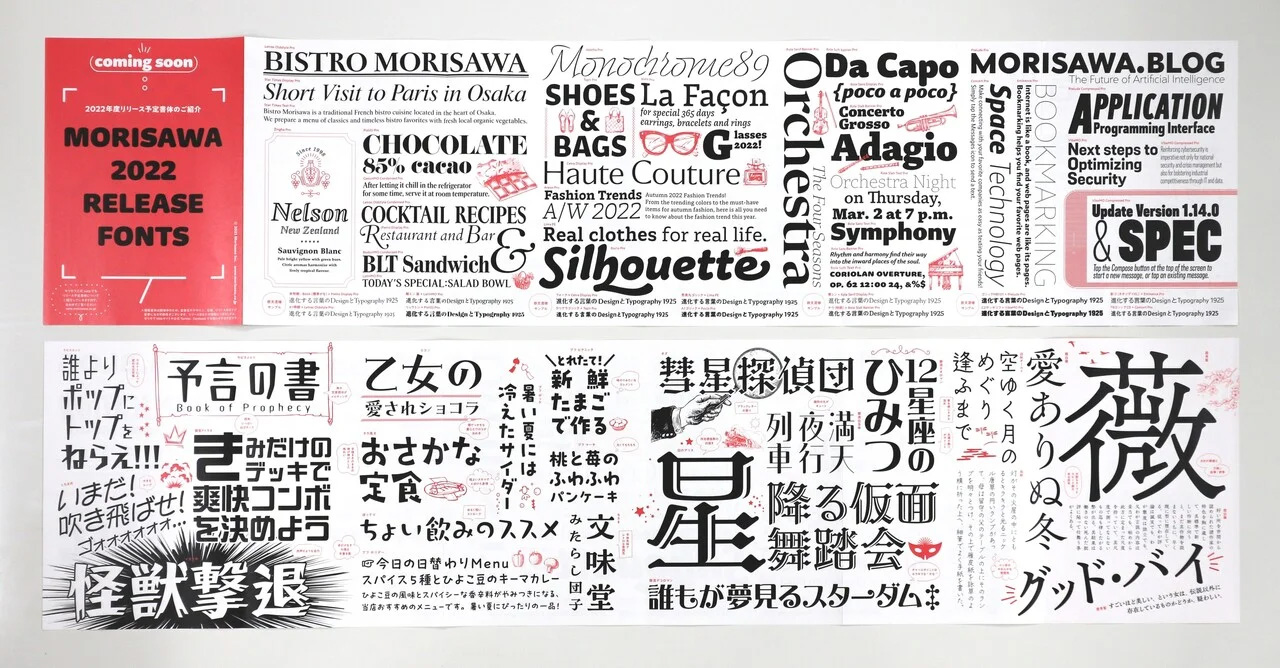
TS Cloud 폰트패키지 이용고객은 모리사와에서 정기적으로 발표하는 신서체를 누구보다도 빠르고 쉽게 별도의 추가요금 없이 사용하실 수 있습니다. 금년도는 모리사와의 지금까지의 기술력을 결집하여, 흐르듯이 문자가 연결되는 필서체 「쵸게츠(澄月)」를 시작으로 개성 풍부한 명조체나 고딕체, 풍부한 웨이트 전개와 편리성이 조화된 라틴알파벳 등 디자인의 폭을 넓혀주는 라인업이 업데이트 되었습니다.